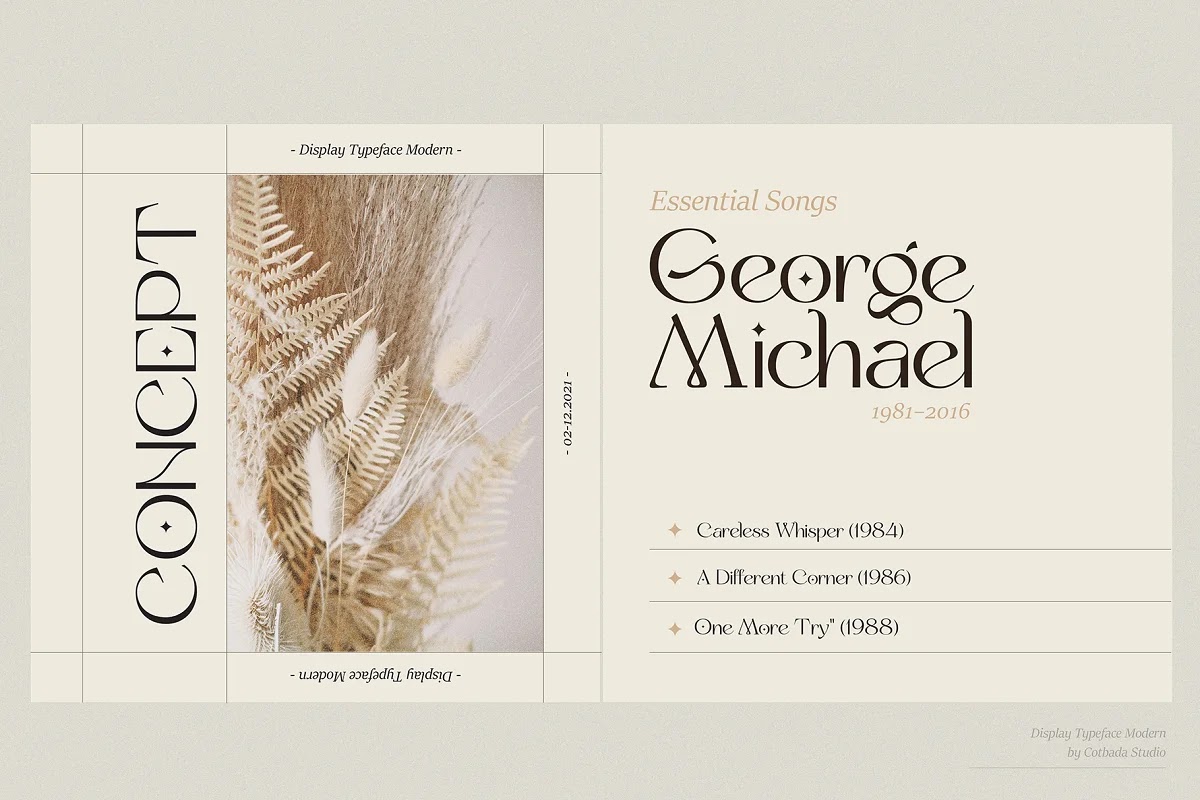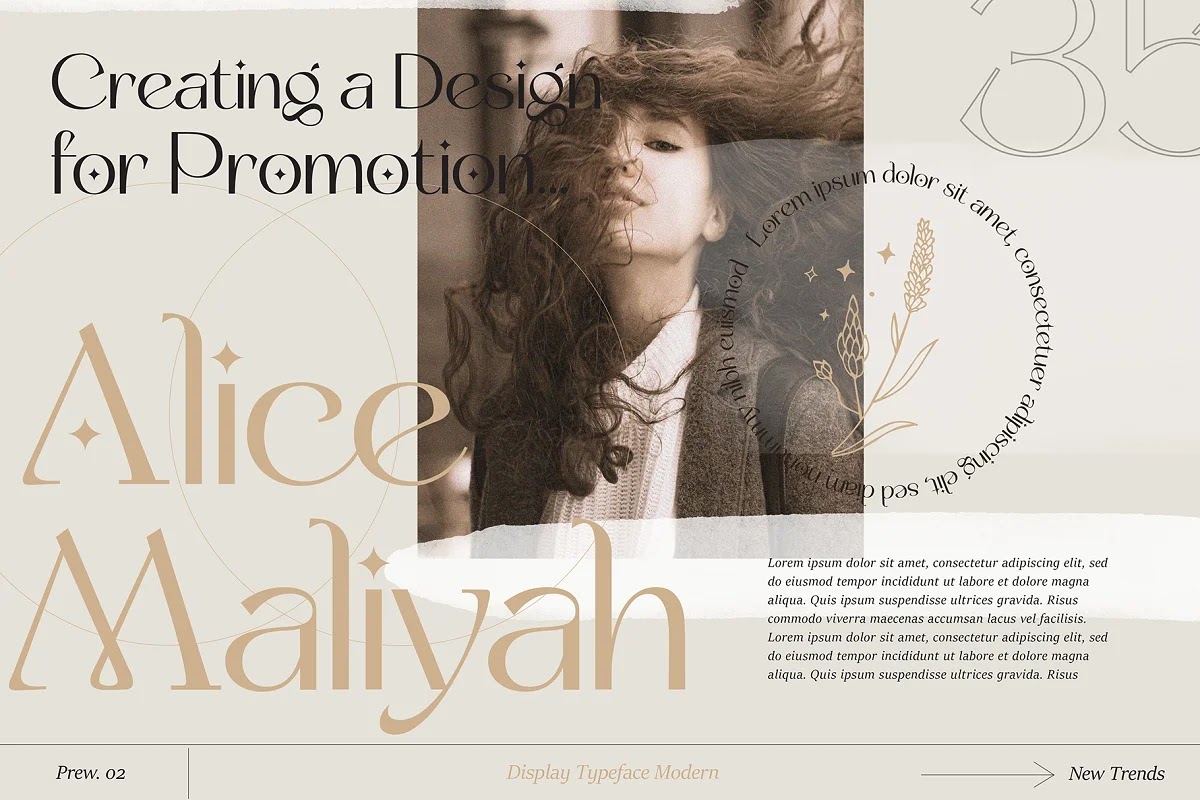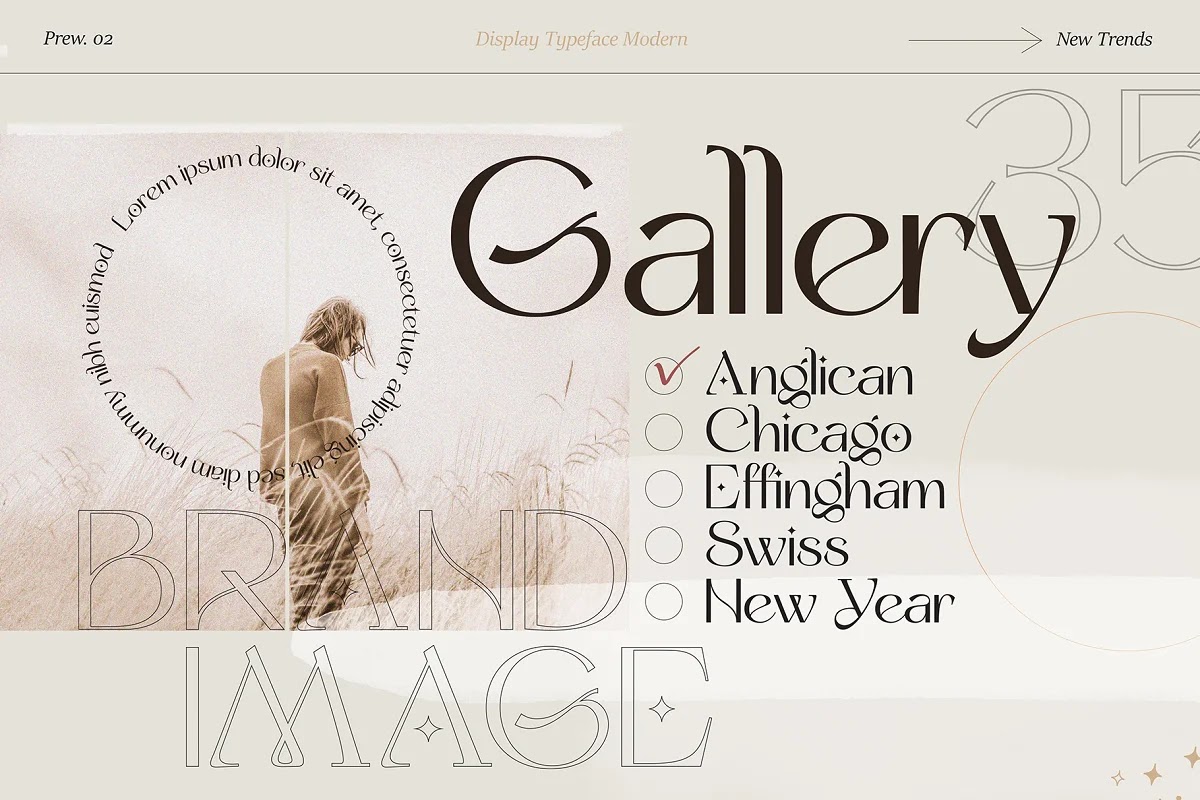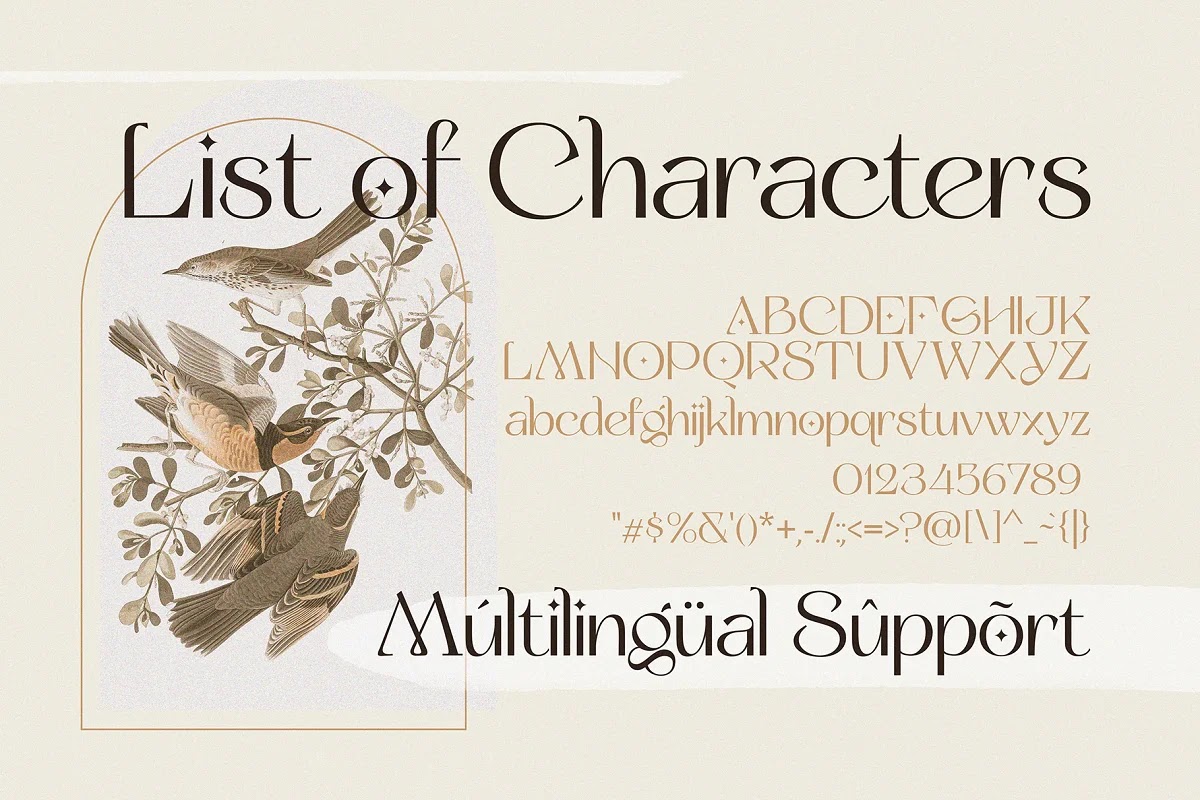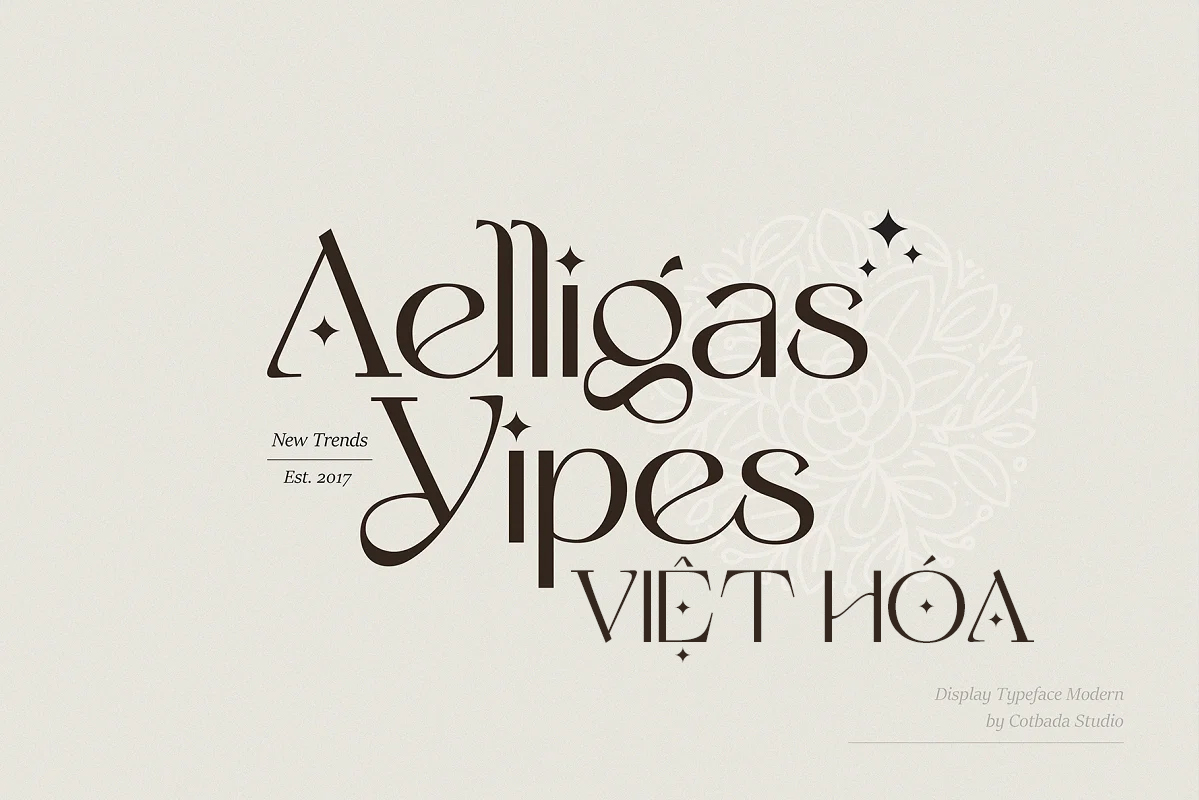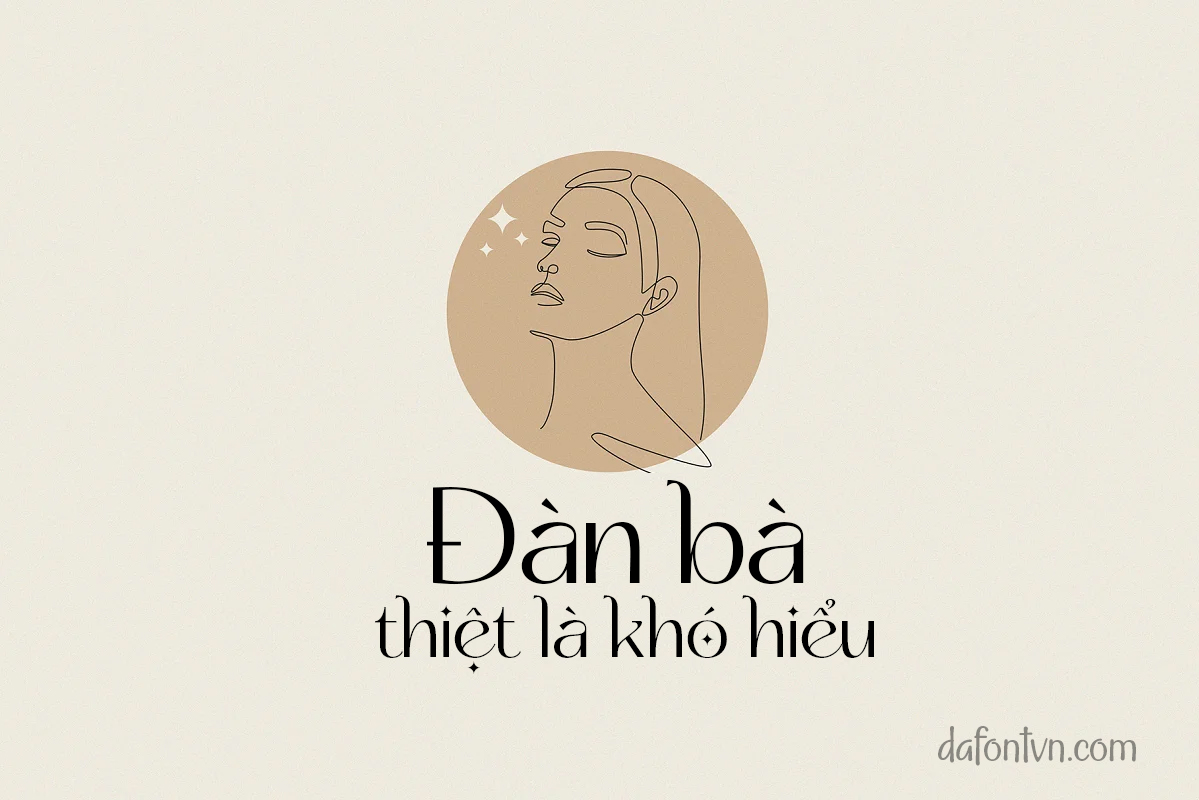
Font Yipes Display Typeface Việt Hóa
Yipes Display Typeface Việt Hóa là một kiểu chữ Display tuyệt đẹp, vừa sang trọng cổ điển vừa hiện đại. Bạn có thể sử dụng để thiết kế lời mời đám cưới, sử dụng nó như một giải pháp thanh lịch cho bố cục tạp chí, thiết kế logo, mẫu powerpoint, trích dẫn teks hoặc chọn Yipes Display Typeface cho bất kỳ đồ họa nào yêu cầu kiểu dáng đẹp với sự tinh tế cổ điển.
– Kiểu chữ hiển thị Yipes Thông thường & Nghiêng
– Chữ hoa
– Ký tự chữ thường
– Hỗ trợ đa ngôn ngữ bao gồm: Pháp, Đức, Tây Ban Nha, Bồ Đào Nha, Ý, Hà Lan, Phần Lan, Thụy Điển, Việt Nam, v.v.